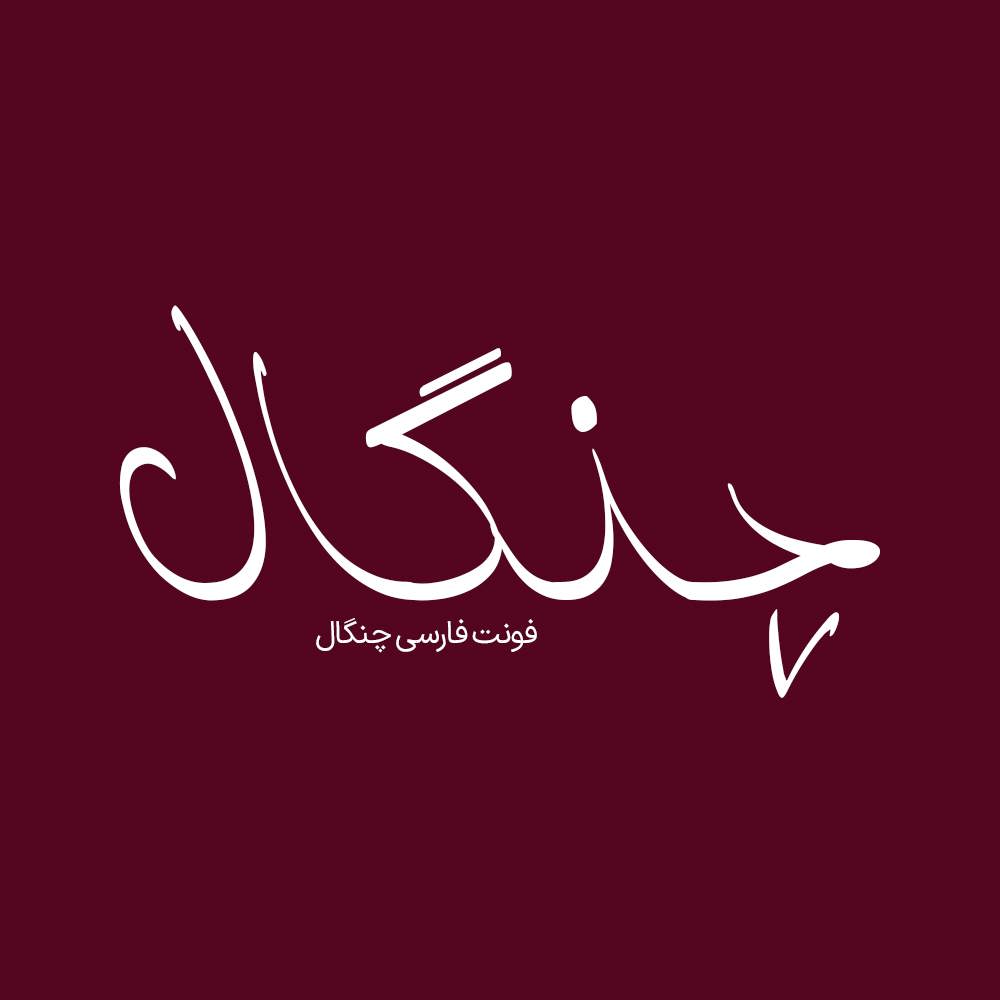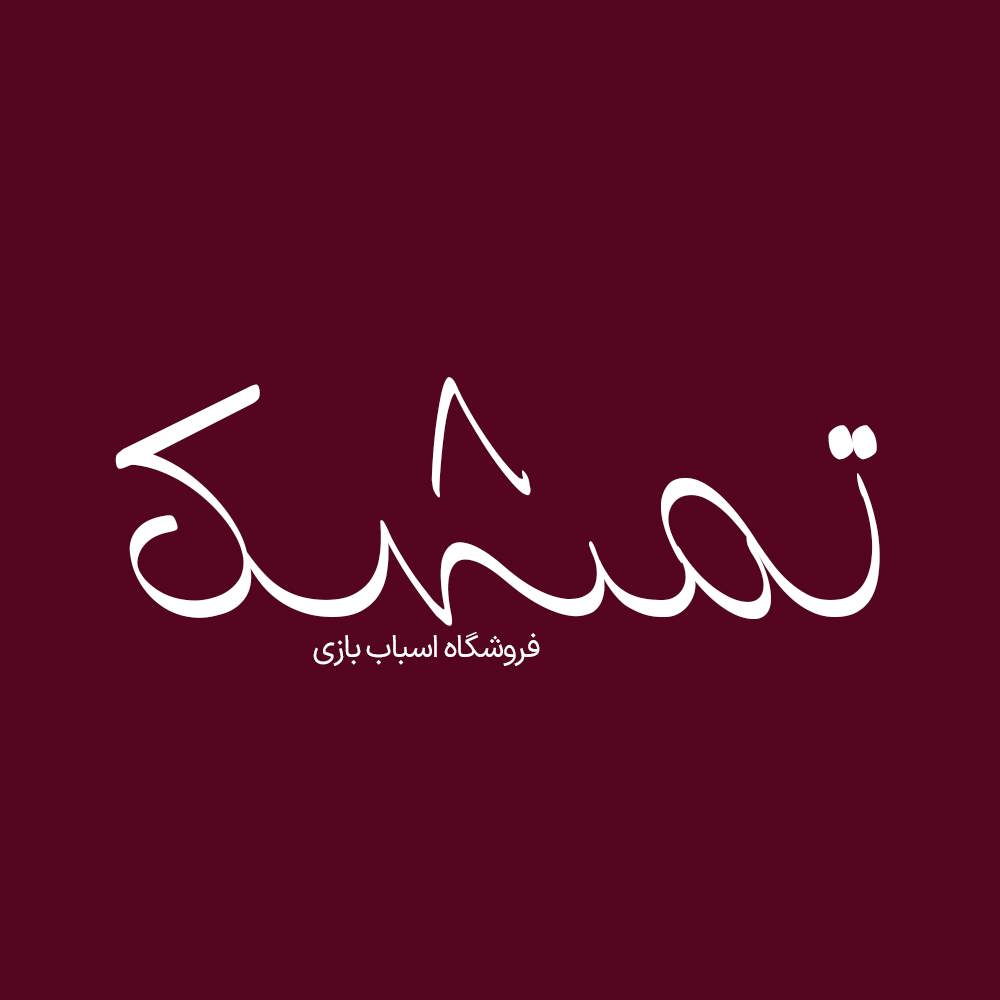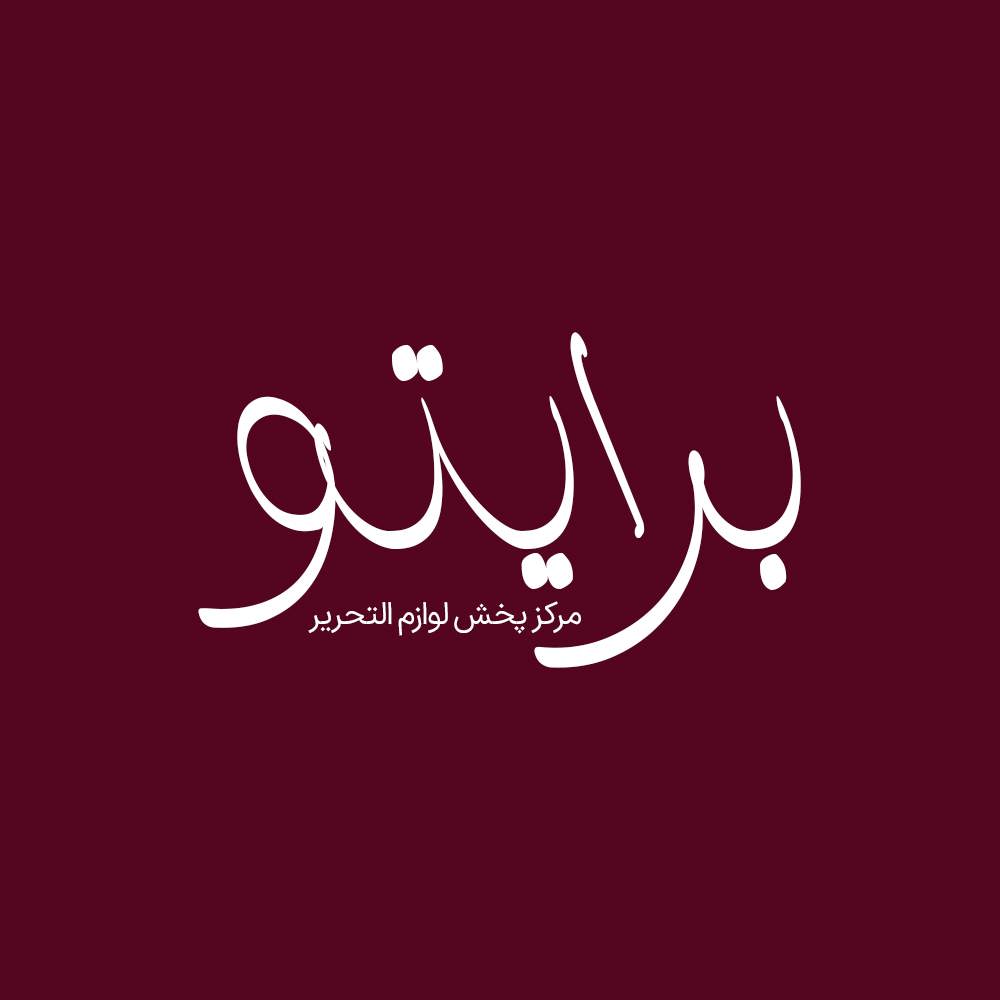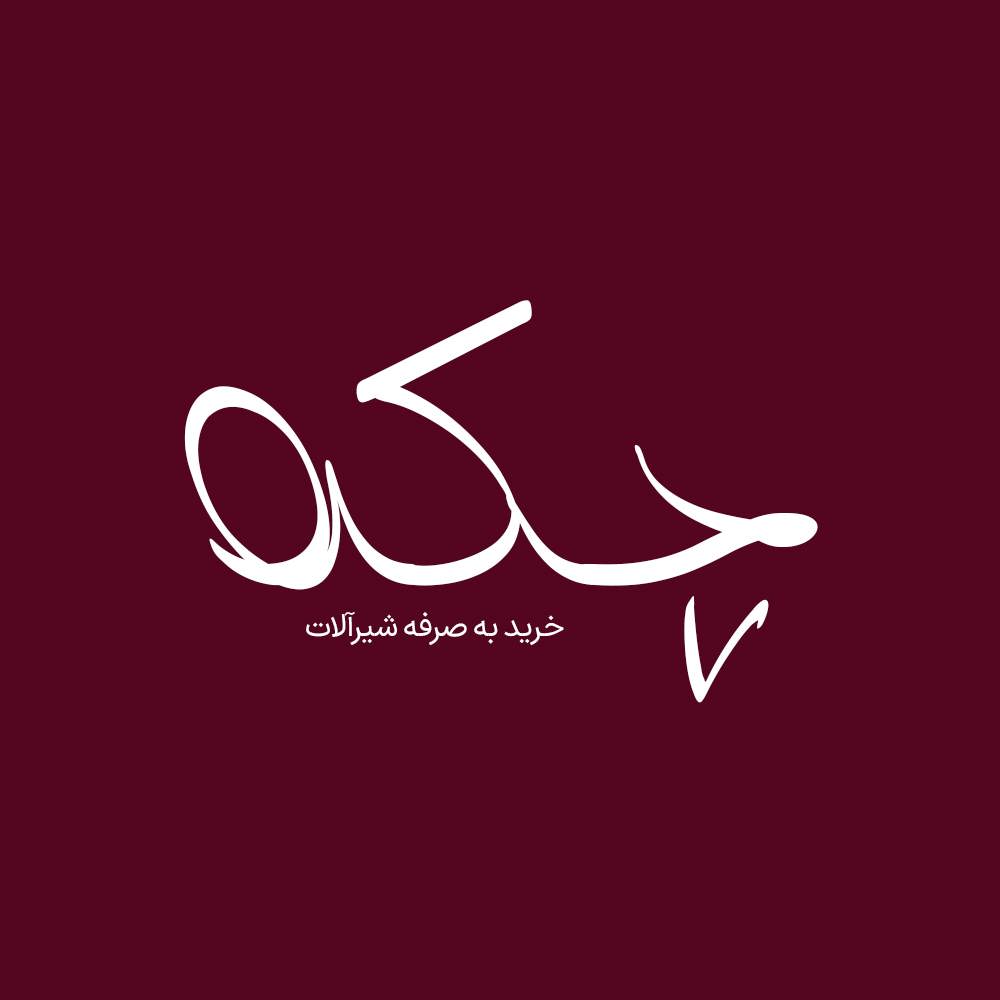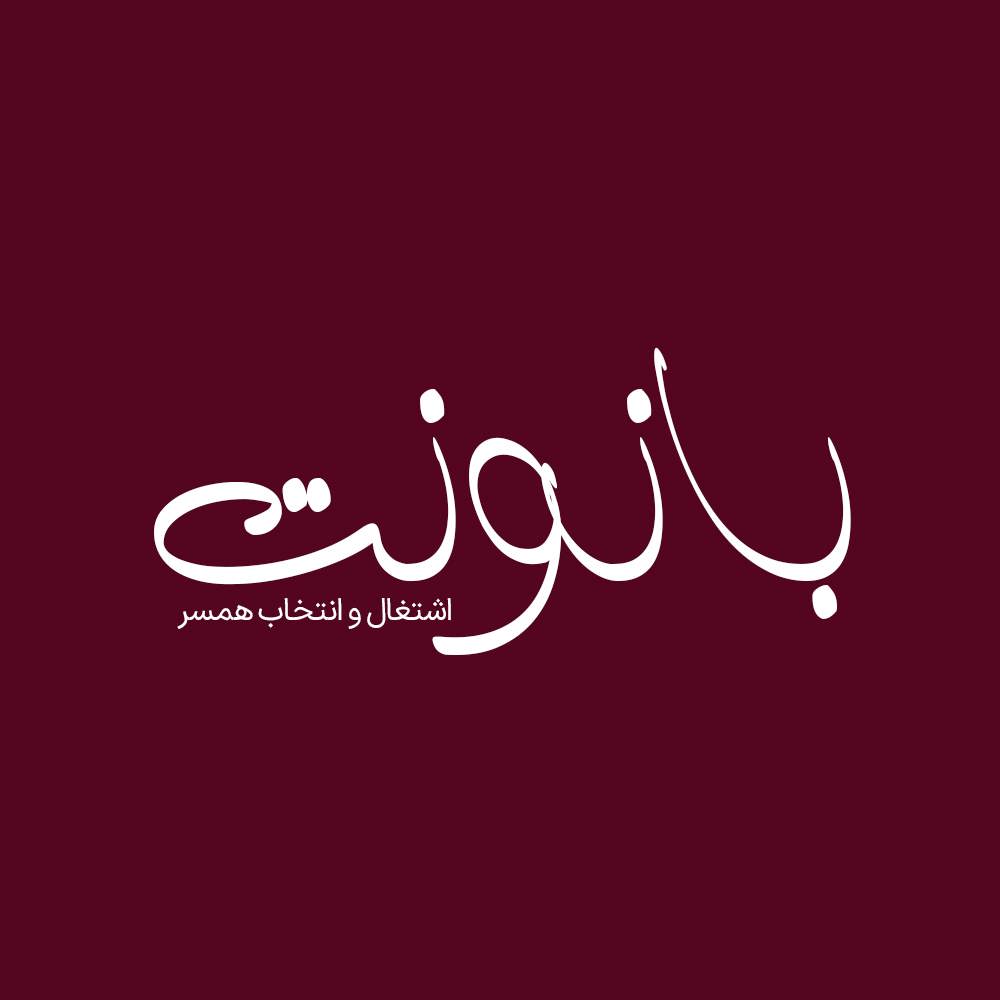
فونت فارسی چنگال Changhal Font
فونت دستنویس چنگال یک فونت بسیار زیبا و حرفه ای و متفاوت برای طراحی انواع امور گرافیکی به خصوص طراحی انواع لوگوتایپ و تایپوگرافی می باشد…
فونت دستنویس چنگال یک فونت بسیار زیبا و حرفه ای و متفاوت برای طراحی انواع امور گرافیکی به خصوص طراحی انواع لوگوتایپ و تایپوگرافی می باشد شما با استفاده از فونت چنگال میتوانید لوگوتایپ و طراحی های زیبایی خلق کنید.
فونت دستنویس چنگال، بهترین فونت دستنویس در هر نرم افزاری می تواند مورد استفاده قرار گیرد اما پیشنهاد میکنیم برای تایپوگرافی بهتر در نرم افزار های گرافیکی (فتوشاپ،ایلاستریتور،کورل و…) استفاده کنید تا با کمی چینش و سفارشی سازی یک خروجی حرفه ای داشته باشید. در ادامه برای شما نمونه تایپ های این محصول حرفه ای رو آماده کردیم که میتونید مشاهده کنید.
پیشنمایش و نمونه تایپ های فونت چنگال